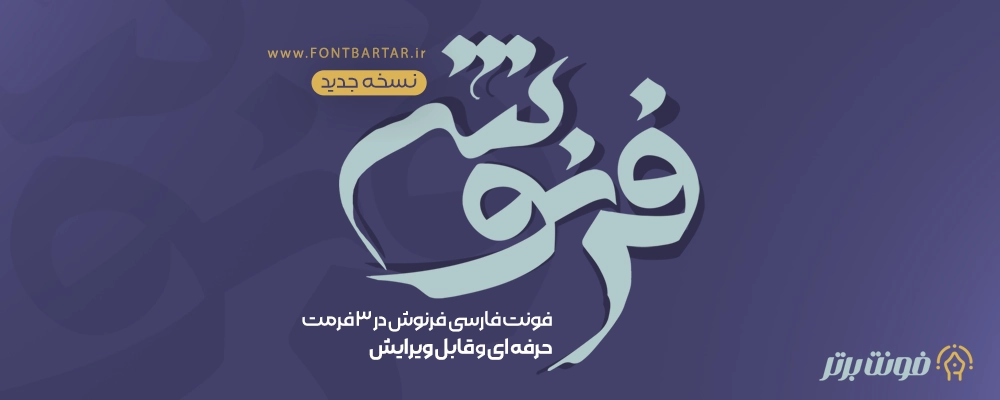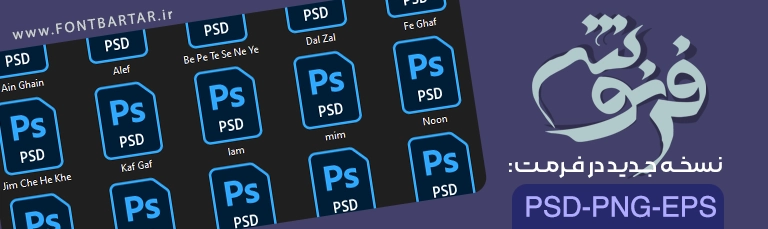
فونت فارسی فرنوش
Farnosh Font
فونت فارسی فرنوش
Font PSD Farnosh Farsi
فونت لایه باز فرنوش یکی از جدیدترین و زیباترین فونت‌های فارسی است که با طراحی خلاقانه و ترکیبی از سبک مدرن و کلاسیک، گزینه‌ای فوق‌العاده برای طراحان گرافیک، تولیدکنندگان محتوا، تایپوگرافی و حتی ساخت پوستر و لوگوتایپ به شمار می‌رود. این فونت PSD به‌صورت کامل توسط فونت برتر توسعه داده شده و بهینه‌ سازی آن برای استفاده در وب‌سایت‌ها، اپلیکیشن‌ها و نرم‌افزارهای طراحی انجام شده است.
ویژگی‌های فونت فرنوش
• طراحی خلاقانه و منحصربه‌ فرد در سبک فونت دست‌نویس و هنری
• مناسب برای طراحی پوستر، لوگوتایپ، بنر، جلد کتاب و کاور شبکه‌های اجتماعی
• پشتیبانی کامل از حروف فارسی تمامی حروف الفبا
سریع و بدون دانش تایپوگرافی فقط و فقط با کنار هم قرار دادن حروف گرافیکی.
فونت فرنوش بر خلاف سایر فونت ها به صورت لایه باز بوده (psd) و امکان تایپ مستقیم در نرم افزار ها را ندارد همچنین شامل تمامی حروف از الف تا ی می شود این فونت به چینش های مختلف می تواند در کمترین زمان این امکان را به طراح بدهد که یک لوگو تایپ حرفه ای برای کسب و کار های مختلف طراحی کند.
فونت لوگوتایپ فرنوش